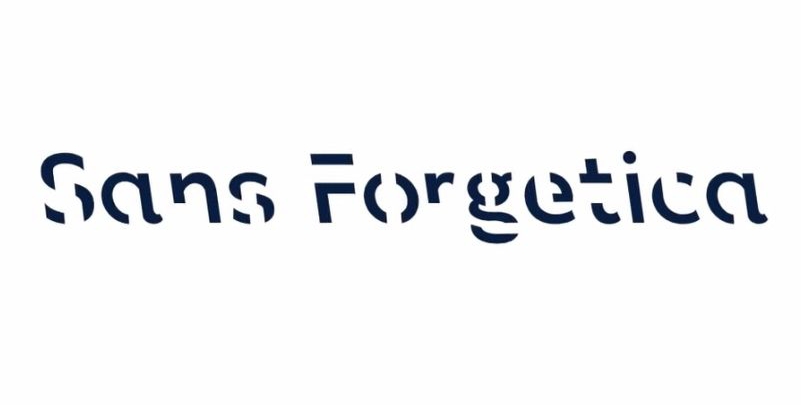
Telset.id, Jakarta – Para peneliti dari Universitas RMIT Melbourne, telah telah membuat font baru, yang disebut ‘Sans Forgetica’. Dalam laporannya yang dirilis ke publik, para peneliti mengatakan bahwa font baru ini dapat meningkatkan memori.
Biasanya, ketika Anda mengetik sebuah catatan, Anda akan mudah untuk melupakan apa yang baru saja diketik, beberapa menit yang lalu.
Namun, seperti dilansir Telset.id dari Mirror.co.uk, tipografi baru ini diklaim dapat membantu Anda mengingat catatan yang diketik lebih lama.
Itu sebabnya para peneliti dari RMIT University di Melbourne ini menyebut font baru yang mereka ciptakan ini dengan nama ‘Sans Forgetica’.
Font baru ini menampilkan huruf yang tampak teriris dan ditulis dengan tujuh derajat kemiringan. Hal ini membuat kalimat menjadi sulit untuk dibaca, namun ini sebenarnya adalah kunci untuk meningkatkan ingatan Anda.
“Ketika kita ingin belajar sesuatu dan mengingatnya, ada baiknya menambahkan sedikit “gangguan” ke proses pembelajaran itu, karena jika sesuatu terlalu mudah, maka itu tidak membuat jejak memori,” kata pengajar pemasaran senior di RMIT, Janneke Blijlevens.
Akan tetapi, apabila terlalu sulit, juga tidak akan meninggalkan jejak memori juga. Sehingga, yang perlu dilakukan adalah mencari titik ‘gangguan’ yang sesuai.
Selama uji coba, para peneliti menunjukkan hasil 400 catatan siswa, yang beberapa ditulis dalam font Sans Forgetica, dan yang lain ditulis dalam font Arial.
Hasilnya mengungkapkan bahwa 50 persen ingat catatan yang ditulis dalam Arial, dan 57 persen ingat dengan catatan yang ditulis menggunakan Sans Forgetica.
“Pikiran secara alami akan berusaha untuk menyelesaikan bentuk-bentuk itu dan dengan melakukan itu memperlambat membaca dan memicu memori,” kata Stephen Banham, seorang dosen tipografi yang ikut membantu mengembangkan font keren ini.